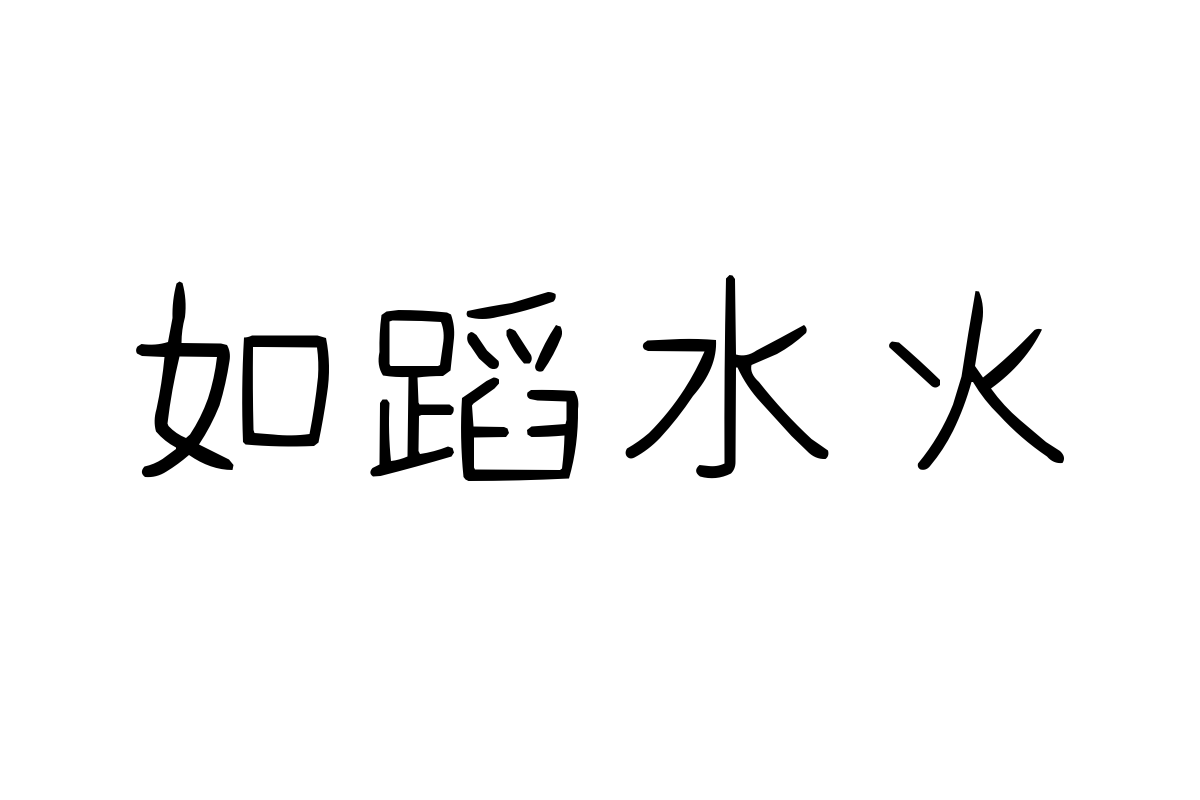
汉仪PP体简是一款由汉仪公司推出的免费字体,具有现代、简洁、易读的特点。这款字体适用于各种商业和设计场景,如广告、海报、包装、网站等。
汉仪PP体简的笔画流畅,字形规整,易于识别和记忆。它的线条粗细适中,既有力量感,又不失柔和,适合用于标题和正文的文字。同时,这款字体的间距均匀,整体协调,给人一种舒适的感觉。
此外,汉仪PP体简还具有一定的艺术性,可以通过不同的排版和组合,展现出不同的视觉效果。无论是简约风格还是复古风格,都能轻松驾驭。
总的来说,汉仪PP体简是一款非常适合现代商业设计和创意表达的免费字体。